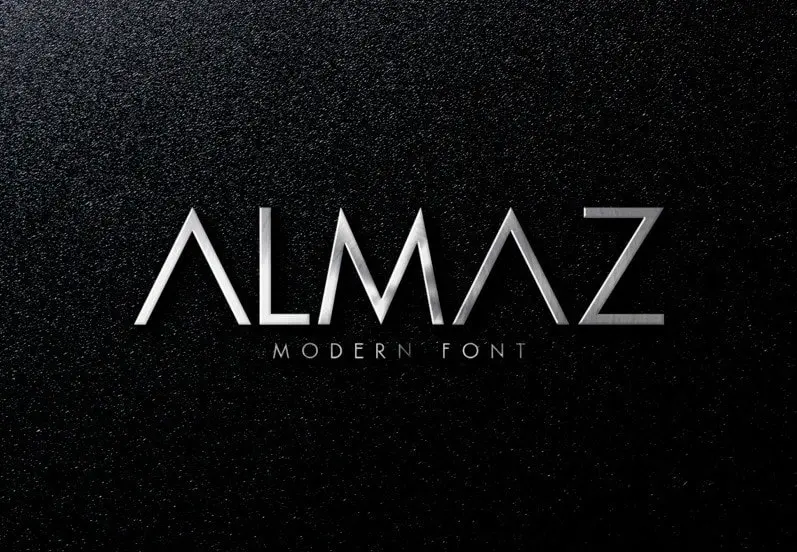
Introduzimos a Almaz Display Font, uma fonte sans-serif futurista criada pela Almaz.id com nuances fortes e desafiadoras. É perfeitamente adequado para títulos, tipografia, roupas, painéis publicitários, revistas, panfletos de marketing, embalagens e websites, ampliando a modernidade e profissionalismo de seus designs. A Almaz Display Font é um alívio ao olhar para projetos digitais e impressos que buscam criar uma aparência distinta e imponente. Suas linhas agressivas e geometrias clean são ideais para destacar elementos-chave em design gráfico, seja na forma de empolgantes títulos ou elegantes fontes de texto. Esta fonte é uma escolha sólida para quem busca adicionar um toque único ao seu trabalho, combinando clareza com sofisticação. Com a Almaz Display Font, você pode explorar novas maneiras de apresentar seus designs digitais e impressos. Seja na web ou em revistas, panfletos ou embalagens de produtos, sua criatividade se torna ainda mais poderosa quando escolhida para combinar com esta fonte alegre e funcional. O design moderno e profissional da Almaz Display Font lhe permite criar um impacto imediato em qualquer mídia visual, sem sacrificar a qualidade ou clareza de suas mensagens. Compreender as nuances desta fonte vai lhe dar uma vantagem competitiva na era digital, onde cada design conta mais do que nunca.